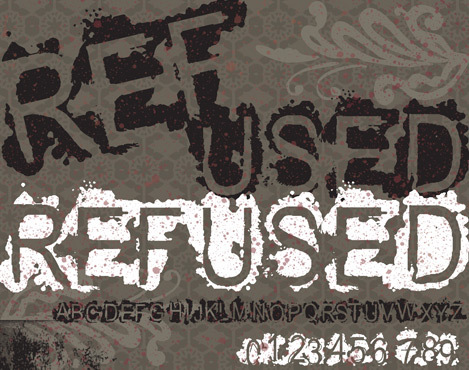
由 Douglas Vitkauskas 设计的 VTKS Refused 是一款免费的“做旧”(distressed)风格标题字体,带有浓厚的朋克传单气质。大写字母看起来像是被刮擦、污损并经历过侵蚀,边缘粗糙且带有残缺,让字形呈现出一种沧桑感,而非规整的描绘。
这种斑驳的质感非常适合海报、专辑封面、杂志内页(Zine)、夜店海报及标题设计,能让文字散发出张扬且不羁的个性。作为一款免费字体,它也十分适用于短标题、乐队 Logo 和抗议风格的图形设计,因为字体本身就自带那种“破损”的氛围,无需过多装饰即可独当一面。